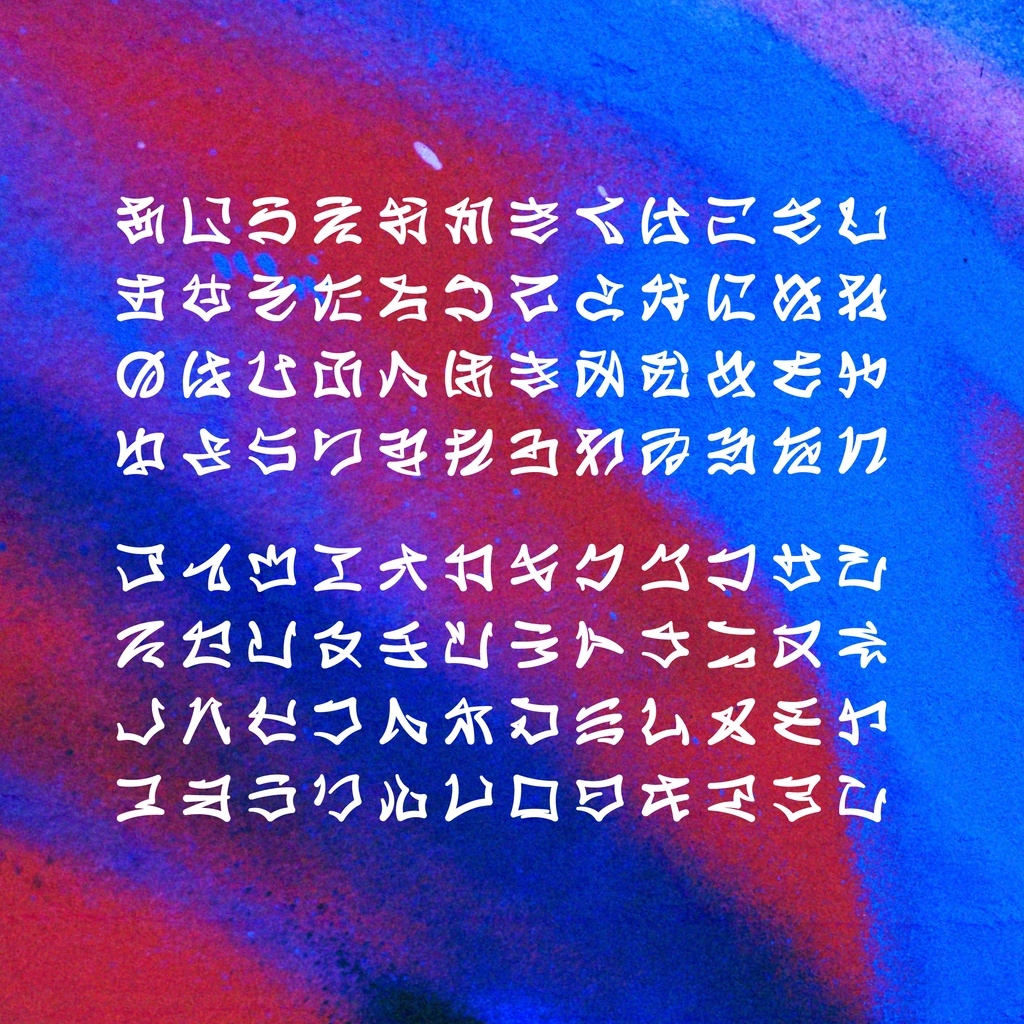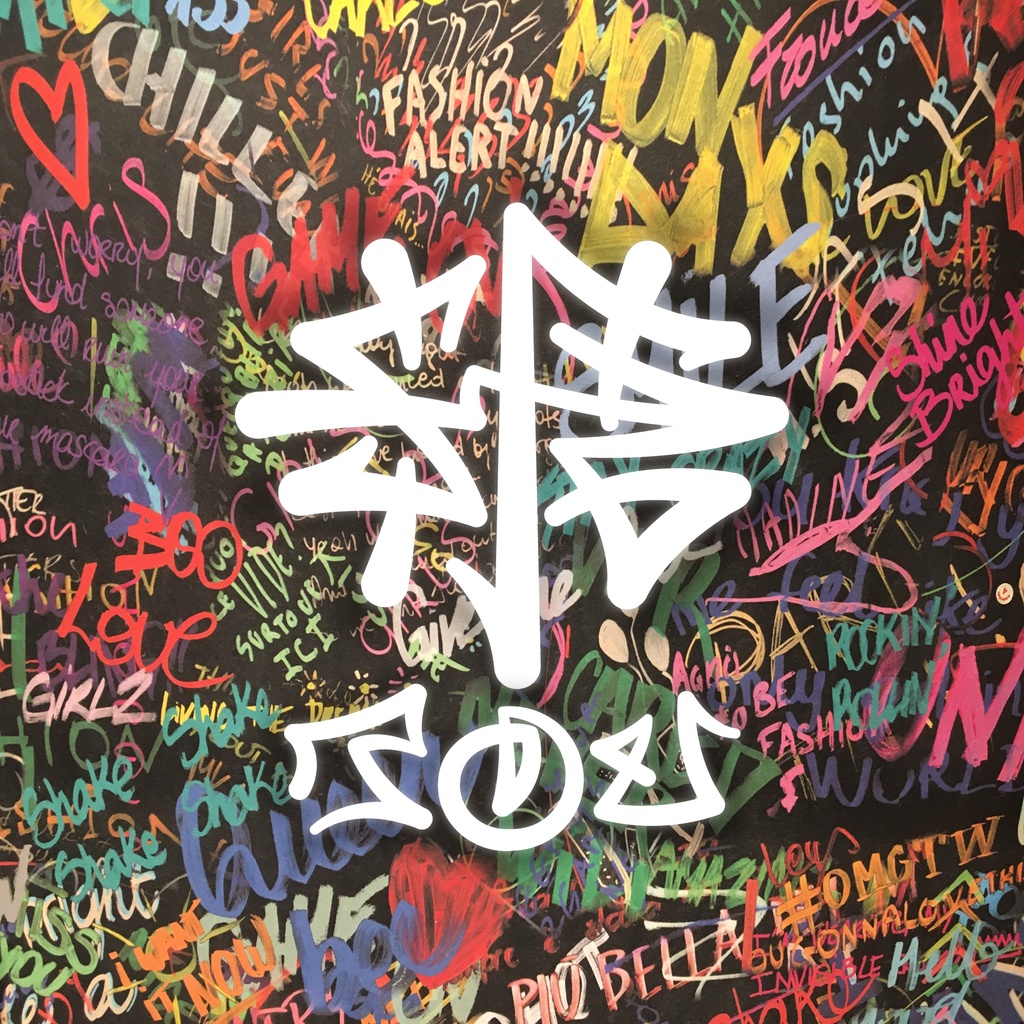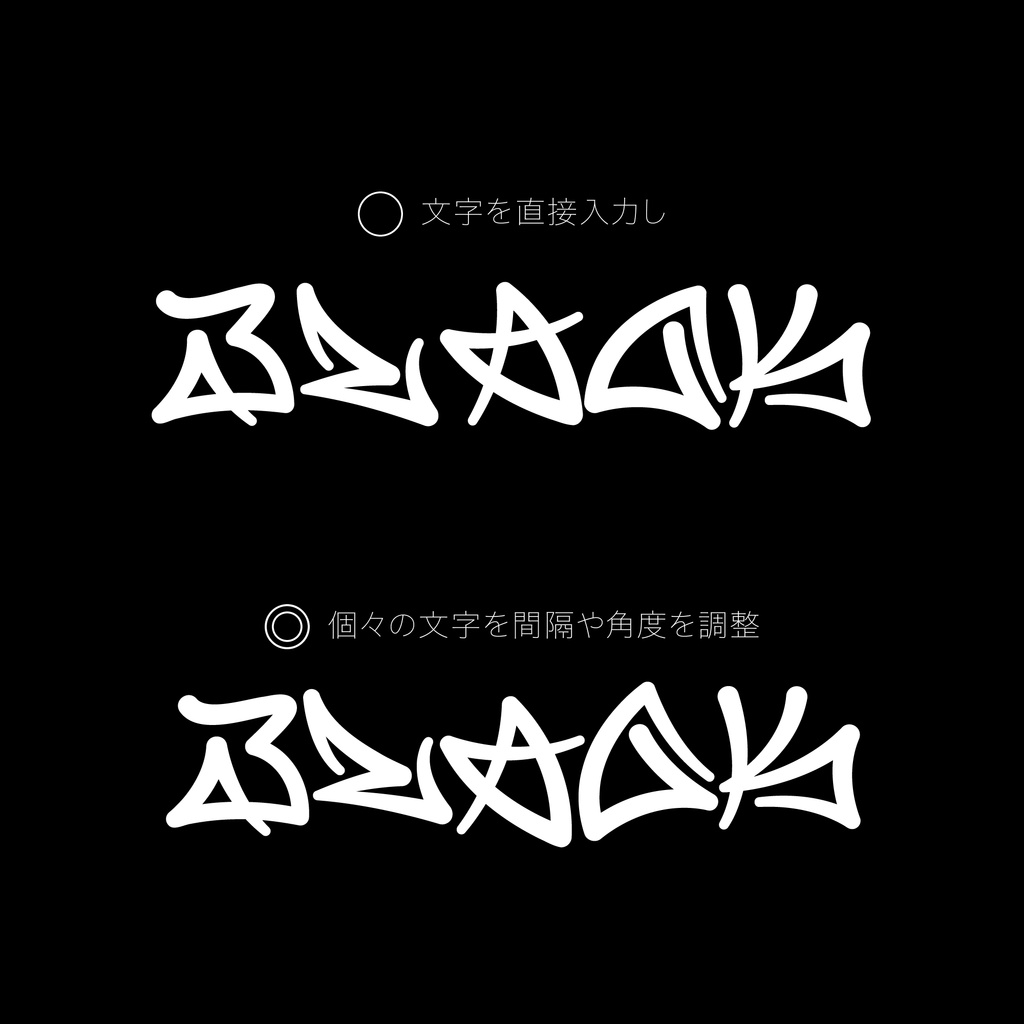
【日本語フォント】糖TOU 「配布ツイートが100RTの倍数達成でもう1ヶ月無料」
🍬 糖/TOU 🍬 📢📢📢📢📢📢📢📢📢 特記事項 📢📢📢📢📢📢📢📢📢 ✨新しいフォントの掲示ツイートが目標達成から1ヶ月間無料配布。その後、配布ツイートが100RTの倍数達成でもう1ヶ月間無料配布する企画を開催中✨ https://twitter.com/amari_design/status/1622805797179883520?s=20 📢📢📢📢📢📢📢📢📢 デザイン説明 📢📢📢📢📢📢📢📢📢 文字の再現性を確保しつつ、画数の間隔に重視、視覚的なバランスを追求しました。 📢📢📢📢📢📢📢📢📢 利用規約 📢📢📢📢📢📢📢📢📢 個人、商用どちらでも利用可能です。 ❤️フォントが使用されたら、ツイッターにお知らせくださいhttps://twitter.com/amari_design❤️ 本素材を使用した作品については、リツイートなどの形で宣伝させていただく場合があります。 フォントのインストール等の技術的なサポートはいたしません。使用して発生したと思われる如何なる問題についても、作者は責任を負わないものとします。 著作権を放棄することはありません。 商標を登録したり、作者であると主張したり、データ自体を販売または再販したりすることは禁じられています。 このコンテンツの最終的な解釈権は作者に帰属します。 内容補充とバージョン更新は製作続けるです。使用する際は最新バージョンにご注意ください。 📢📢📢📢📢📢📢📢📢 収録內容 📢📢📢📢📢📢📢📢📢 ラテン文字、数字、仮名だけてを含む290グリフが含まれています。 ーーーーーーーーーーーー Twitter:https://twitter.com/amari_design Behance:https://www.behance.net/9f45706b ーーーーーーーーーーーー